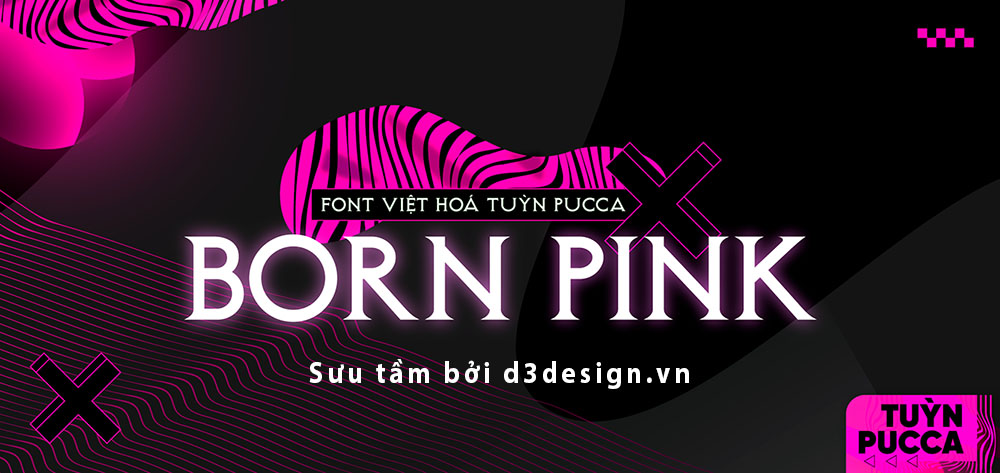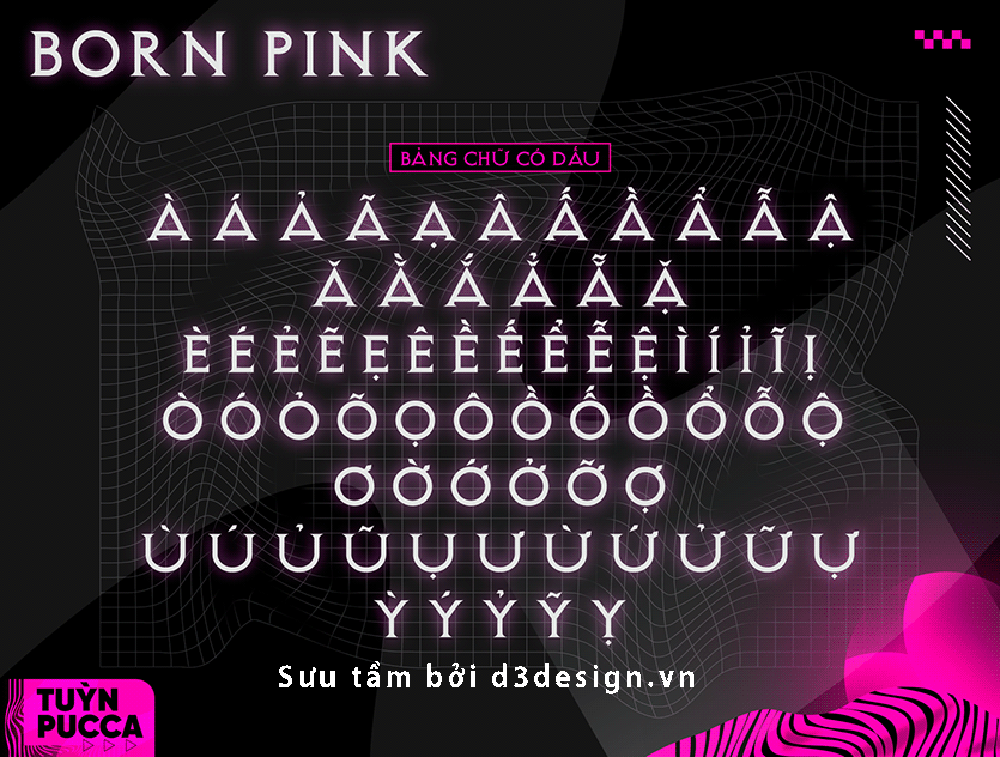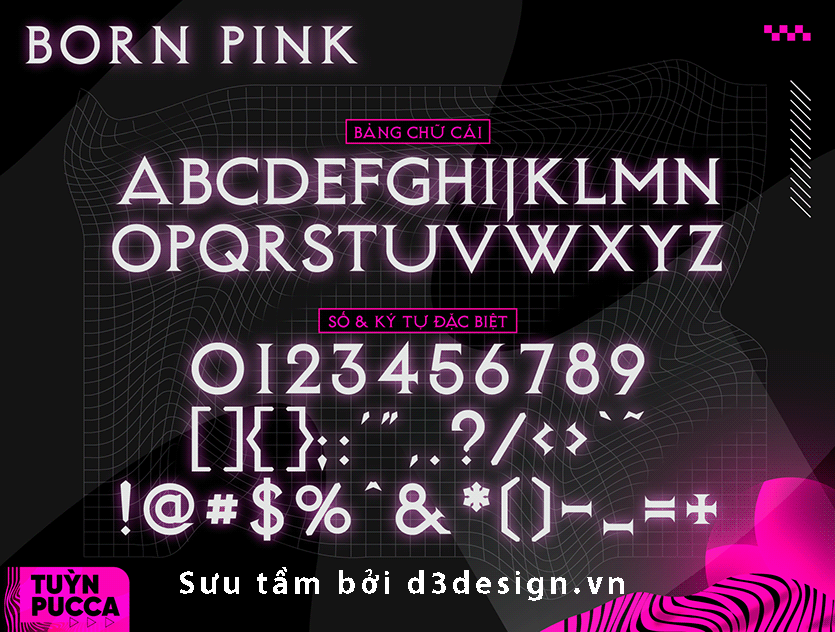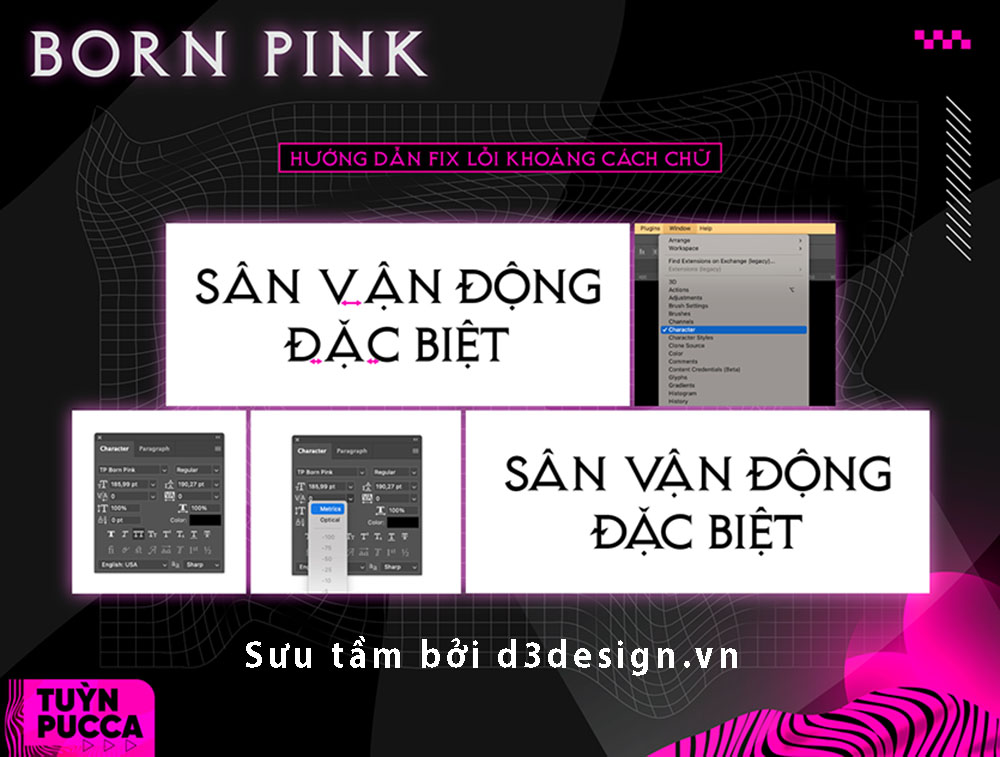
Font Việt Hóa - Born Pink Poster Concert BORN PINK BLACKPINK
Phông chữ được phát triển dựa trên phông chữ Exocet và lấy cảm hứng từ dòng chữ trên poster concert BORN PINK của nhóm nhạc nữ BLACKPINK.
- Font chữ có đầy đủ bộ số và đã được việt hóa
- Phù hợp với xu hướng BORN PINK